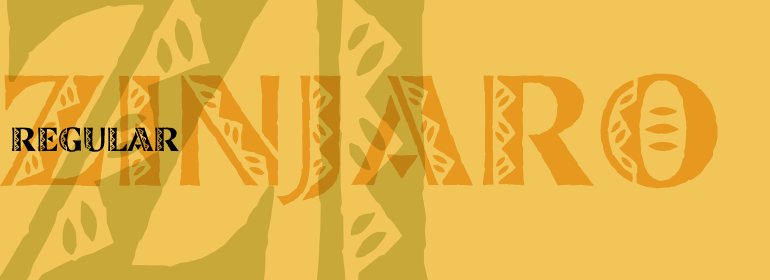
Zinjaro™
Zinjaro™,这款字体结构工整、笔画清晰,兼顾美观与易读性,适用于标题、正文、海报、包装、LOGO 等多种场景。字形优雅稳定,风格百搭耐看,适配日常排版与创意设计,让文字呈现更舒适、更具质感。Zinjaro™一笔一画,皆是细节,以均衡的比例、流畅的线条打造舒适视觉体验,字形端正大气,风格简约现代。无论是商业设计、品牌宣传还是日常排版,都能轻松驾驭,让文字更有格调与力量。Zinjaro™字体下载。
Zinjaro是英国设计师Carol Kemp的作品。其设计巧妙地借鉴了非洲和拉丁美洲的艺术元素。将带有装饰的大写字母笔划与实心大写字母笔划组合起来让人印象深刻,不可预测的风格和一家族的图案与边框元素进一步增强了字体。
Zinjaro is the work of English designer Carol Kemp. Its clever design captures elements of both African and Latin American art in its forms. A combination of decorated and solid capital strokes gives it an exciting, unpredictable appearance and an array of devices and border elements further enhance the font.